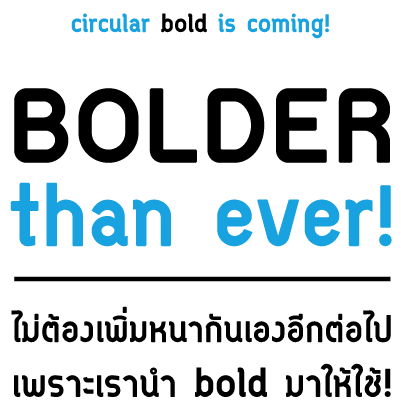
circular â„¢
ฟอนต์เนี๊ยบมากเลย  :25:
สวยสุดยอดเลยครับ ลงตัวมากเลยอะ  :25:
สมแล้วที่ถูกแต่งตั้งให้เป็นหนึ่งใน Avant-garde
โมโม่ ทำ Bold มาให้แล้ว +
มีการเปลี่ยนแปลงนิดหน่อยของ regular ด้วย  :47:
นั่นคือตัว i & l
สมกับทีเป็นเทพไทพ้าจริงๆ :12: